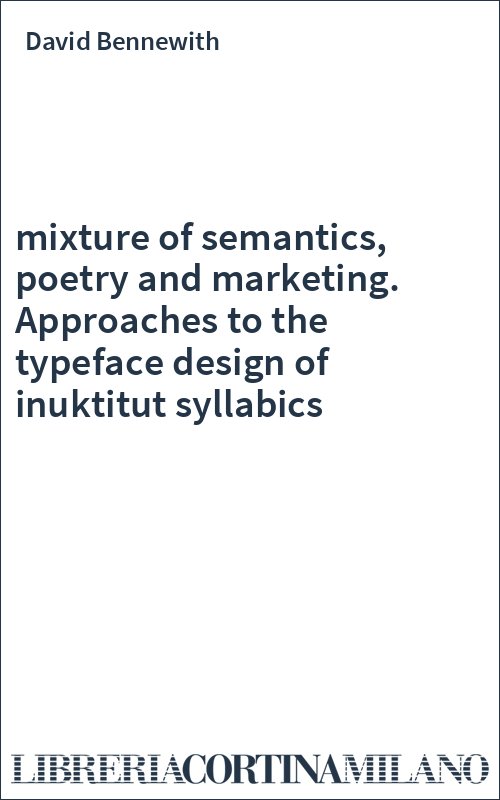
"A mixture of semantics, poetry and marketing. Approaches to the typeface design of inuktitut syllabics" è uno sguardo dettagliato alla storia del design tipografico della scrittura inuktitut. Il periodo analizzato va dall'introduzione da parte dei missionari cristiani, all'inizio del XX secolo, di una lingua scritta, fino all'incorporazione dei suoi parametri su internet.
mixture of semantics, poetry and marketing. Approaches to the typeface design of inuktitut syllabics
| Autore | David Bennewith |